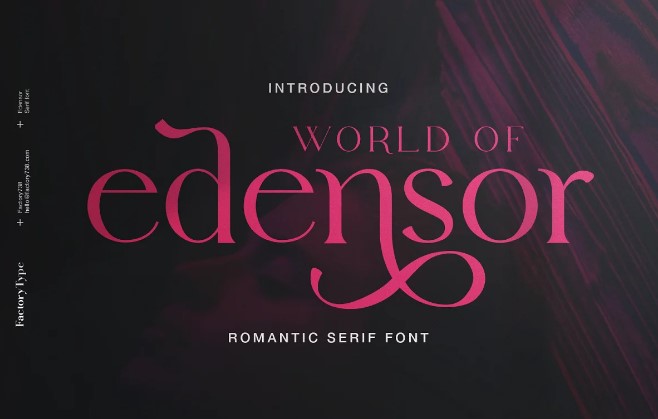
Edensor - это игривый и в то же время романтичный шрифт с засечками. Она дразнит взгляд своими изгибами, но при этом сохраняет стильное спокойствие. Разнообразие начертаний обеспечивает широкий выбор, который поможет вам найти наилучший типографский цвет. Стилистическая вязь и альтернанс предлагают идеальный шрифт для любого вида творчества.
Основные латинские буквы A-Z и a-z
Цифры и пунктуация
Стилистические альтернативы и лигатуры
Многоязычная поддержка ä ö ü Ä Ö Ü ...